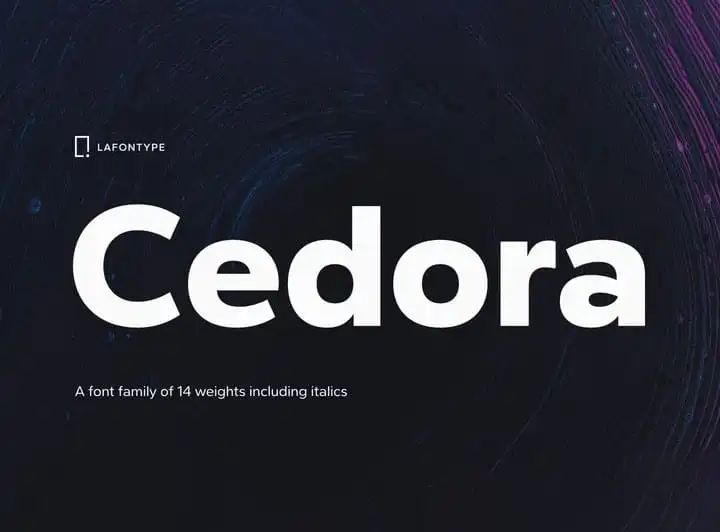
Introduzimos Cedora Sans Serif, uma família de fontes gerais de sans-serif amigável com traços geométricos. Esta famosa é uma redução de suas atributos essenciais. Cedora vem em 14 estilos com sete pesos que vão do fino ao escuro, cada um representando múltiplas línguas e permitindo-lhe realizar atividades editoriais. Cedora Sans Serif é uma opção ideal para designers gráficos devido a sua simplicidade e facilidade de uso. Seja você criando um site elegante ou produzindo materiais publicitários, esta fonte vai manter seu design moderno e contemporâneo. Essa família de fontes vem em uma variedade de estilos diferentes que permitem flexibilidade em sua criação. Além disso, o fato de representar múltiplas línguas torna Cedora muito versátil, permitindo que você atenda a necessidades linguísticas e culturais diversas. Cedora Sans Serif é uma escolha inteligente para qualquer projeto onde você precisa de um design moderno e limpo. Com sua simplicidade, ele oferece um tom amigável sem perder o seu caráter profissional. Seja em sites, cartazes, ou material impresso, Cedora irá fazer sua marca mais atrativa e única.